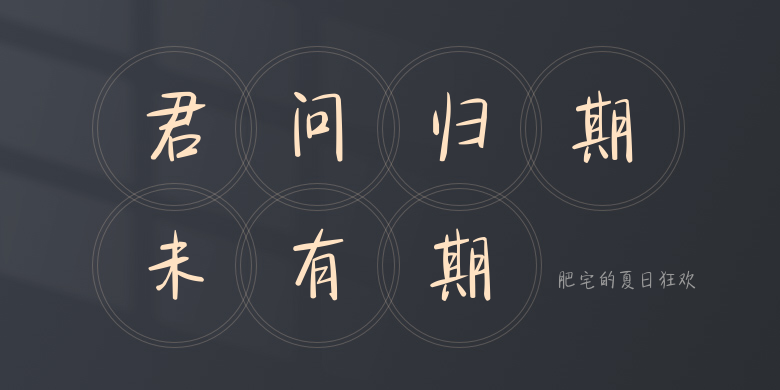
肥宅的夏日狂欢
肥宅的夏日狂欢,这款字体结构工整、笔画清晰,兼顾美观与易读性,适用于标题、正文、海报、包装、LOGO 等多种场景。字形优雅稳定,风格百搭耐看,适配日常排版与创意设计,让文字呈现更舒适、更具质感。肥宅的夏日狂欢一笔一画,皆是细节,以均衡的比例、流畅的线条打造舒适视觉体验,字形端正大气,风格简约现代。无论是商业设计、品牌宣传还是日常排版,都能轻松驾驭,让文字更有格调与力量。肥宅的夏日狂欢字体下载。